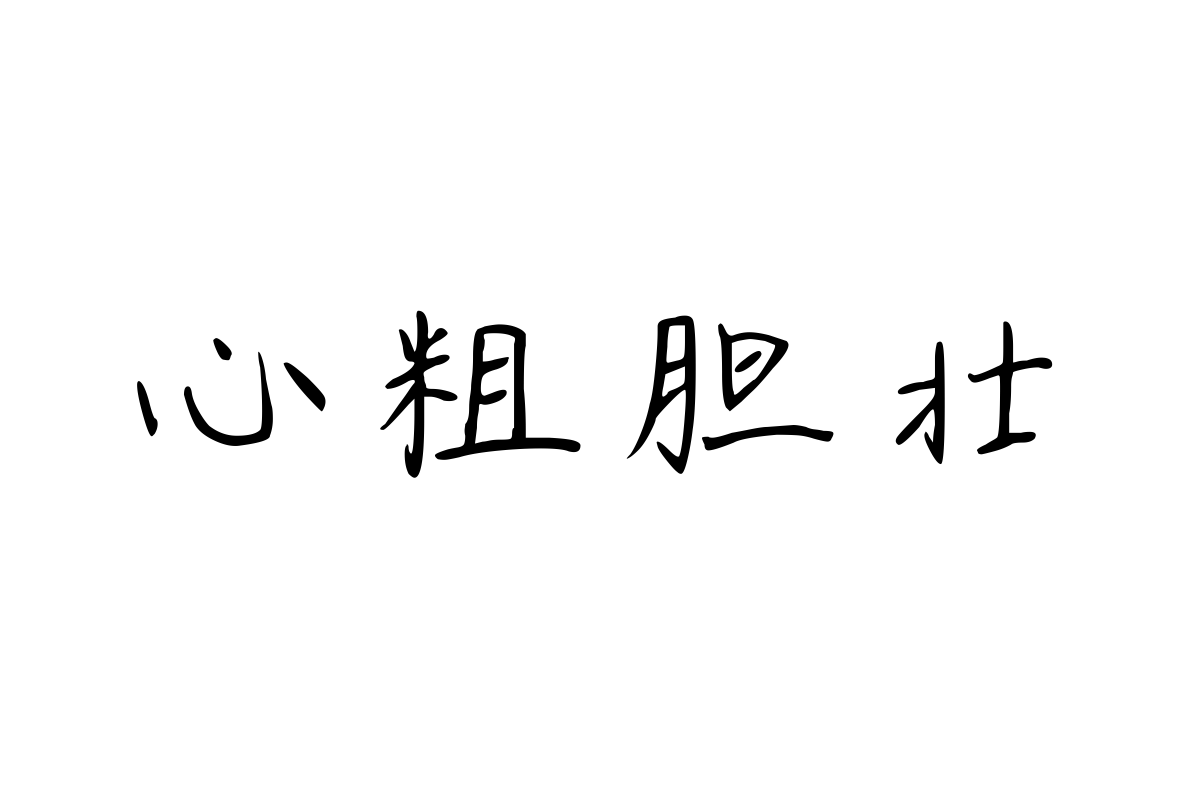
三极沉香楷书字体是一种具有独特风格的中文书法字体,其特点是笔画流畅、结构严谨、字形饱满。这种字体适合用于正式的文档、广告、海报等场合,能够给人留下深刻的印象。
三极沉香楷书字体的特点如下:
1. 笔画流畅:这种字体的笔画线条流畅自然,没有过多的顿挫和转折,给人一种轻松愉悦的感觉。
2. 结构严谨:这种字体的结构严谨,每个字的笔画都有固定的间距和位置,使得整个字体看起来整齐划一。
3. 字形饱满:这种字体的字形饱满,每个字都呈现出一种饱满的感觉,给人一种稳重的感觉。
4. 易于识别:由于这种字体的特点,使得它非常容易被人们识别,适合用于各种场合。
5. 风格独特:三极沉香楷书字体的独特风格,使得它在众多字体中脱颖而出,具有很高的辨识度。